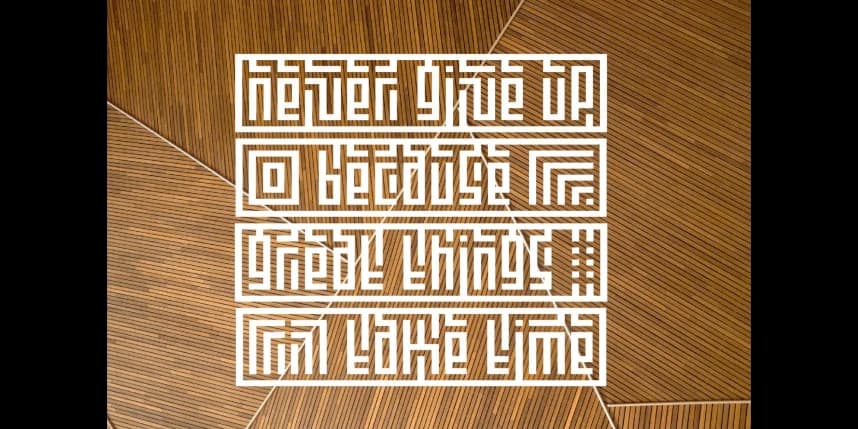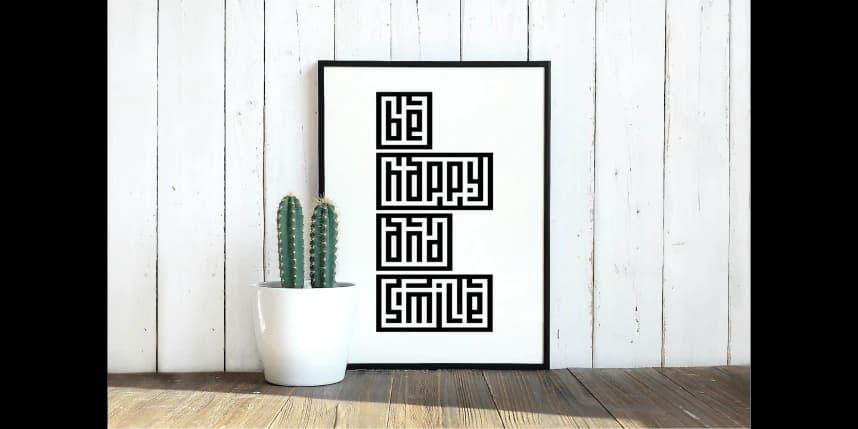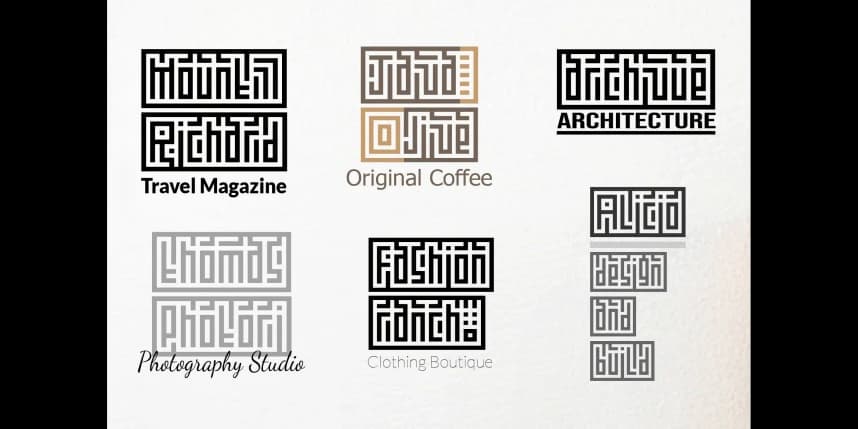
Kufication Root Yazı Tipi
Kufication Root Font, Arap Kare Kufic hat kaligrafisinden ilham alınmış Latin bir gösterim yazı tipidir — İslam görsel tarihinde en geometrik ve yapısal olarak en kesin yazı tiplerinden biridir. Her harf biçimi sıkı bir ızgara sistemine dayanacak şekilde inşa edilmiştir, bu da ona hem zamansız hem d
Kufication Root Font, Arap Kare Kufi hat kaligrafisinden ilham alan Latin bir gösterim yazı tipidir — İslam görsel tarihindeki en geometrik ve yapısal olarak en kesin yazı tiplerinden biridir. Her harf biçimi sıkı bir ızgara sistemi üzerinde inşa edilmiştir, bu da ona hem zamansız hem de çağdaş bir hissiyat veren cesur, mimari bir nitelik kazandırır.